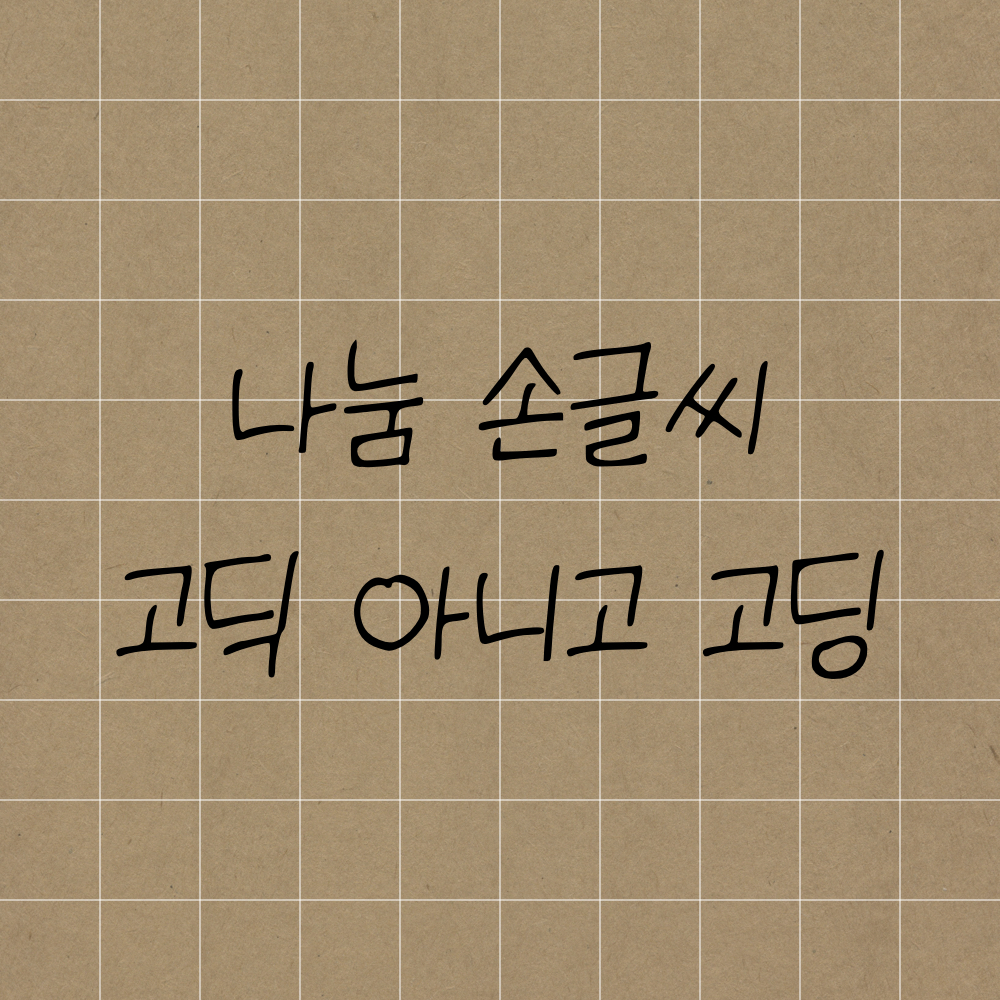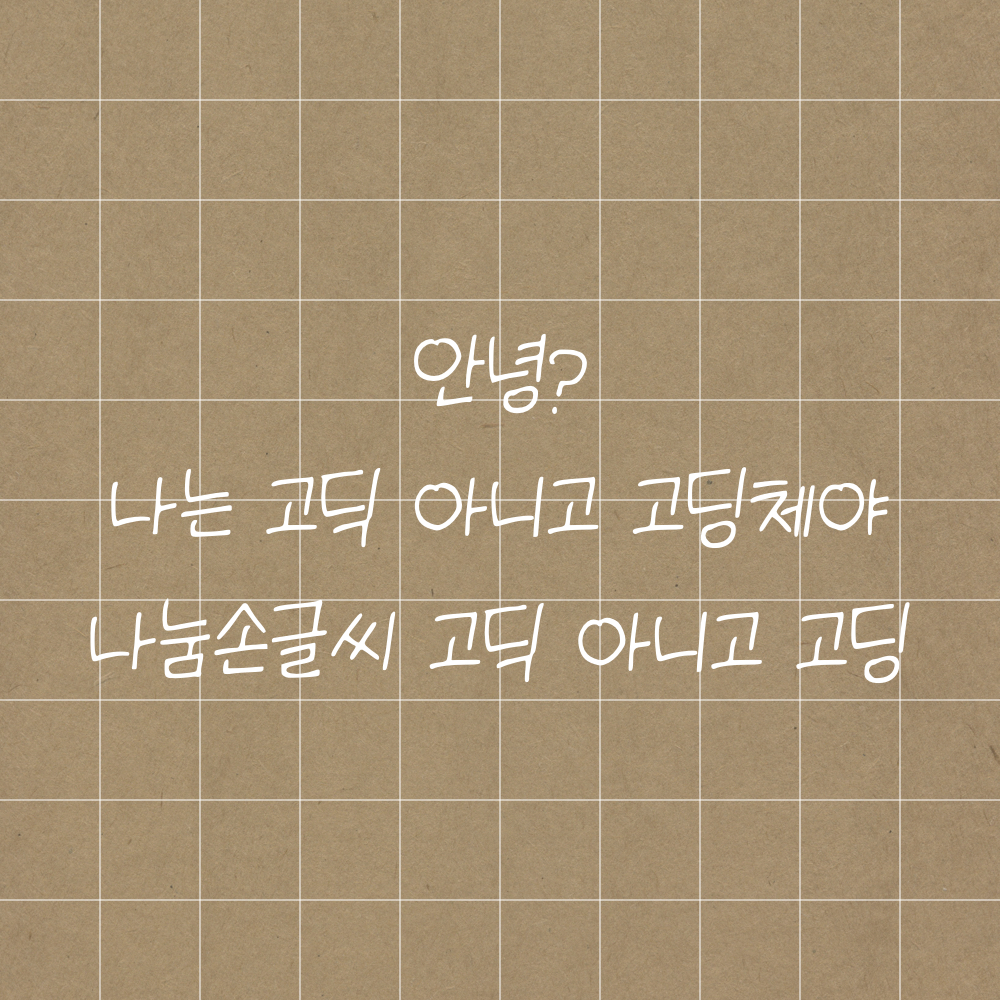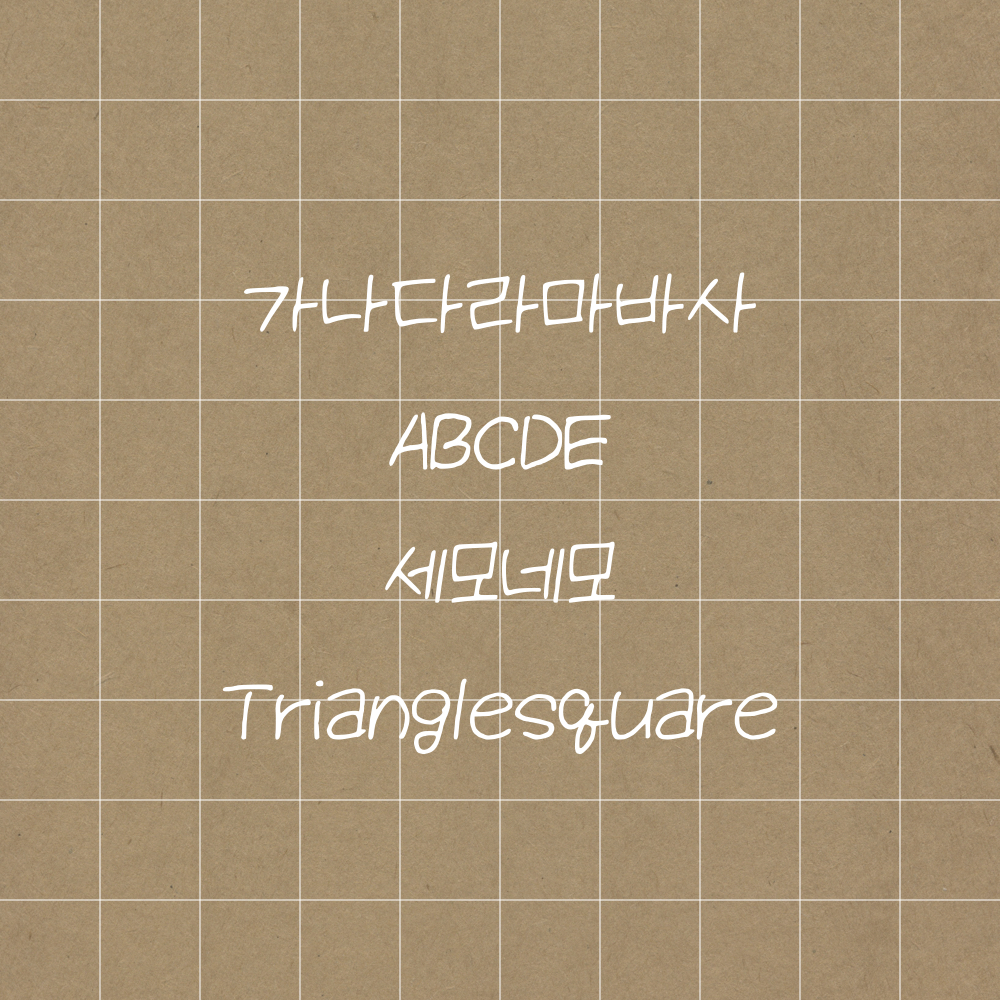
오늘의 폰트는 고딕 아니고 고딩입니다🧡
실제로 있을 법한 글씨체로 디지털 필기이지만 자연스러운 필기에 적합한 폰트입니다.
다른 폰트와 비교할 때 글자의 크기가 커보이는 효과가 있습니다.빼곡한 필기가 좋은 분들께 딱 일지도~?😆
o을 볼 때마다 하트가 보여서 귀여운 맛이 있네요😘
은근히 귀여운 폰트였습니다. 여러분이 찾는 폰트였길 바랍니다⭐️